광고 사인은 단순한 안내판이 아니라, 브랜드의 얼굴이자 메시지를 전달하는 중요한 요소예요. 길거리 간판부터 기업 로고, 공공 안내판까지 다양한 형태로 사용되죠. 사인을 잘 만들면 가독성이 높아지고, 브랜드 이미지도 효과적으로 전달할 수 있어요.
🛑 광고 사인의 기원과 역사
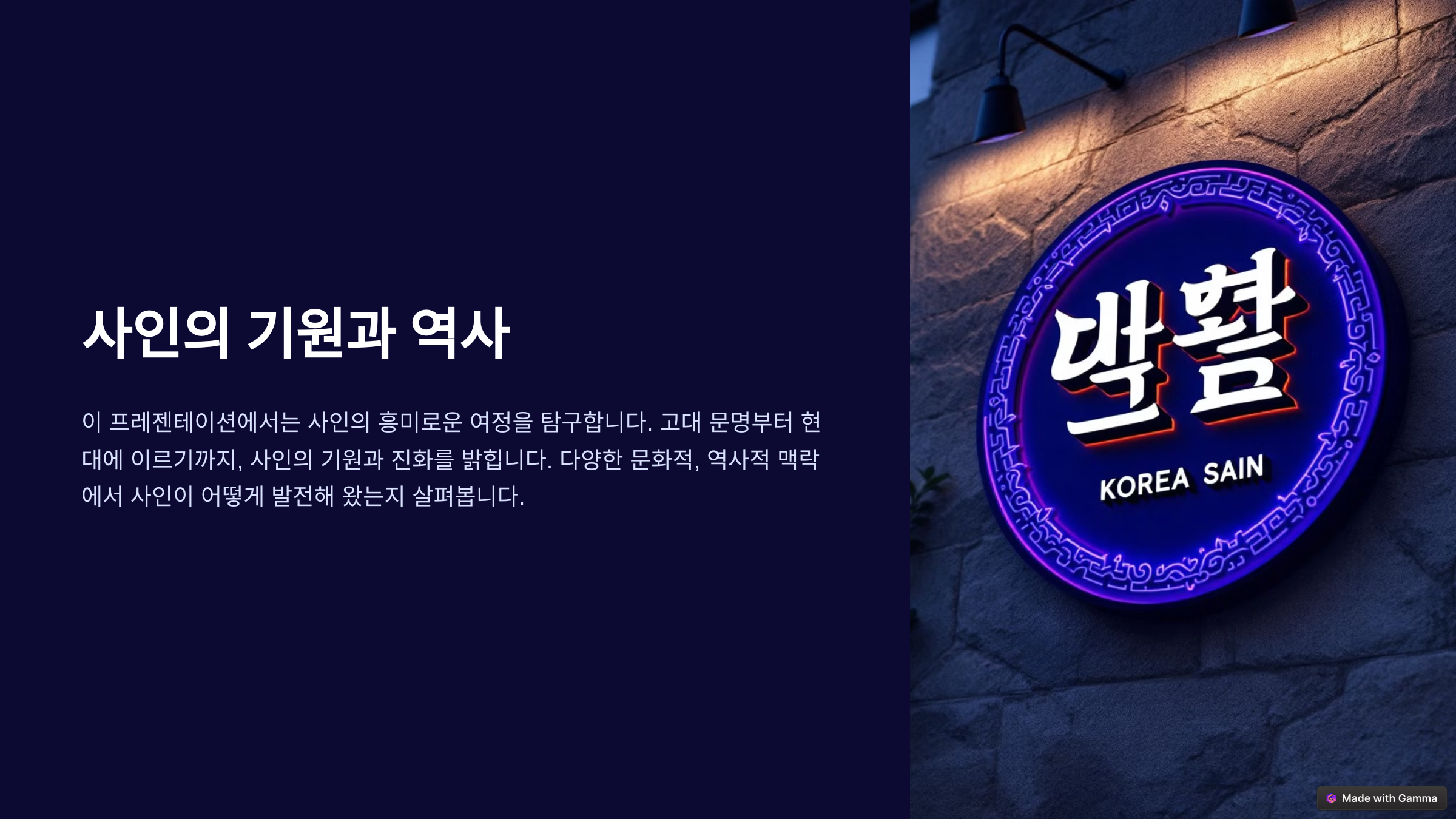
사인의 기원과 역사
광고 사인은 인류가 문자를 사용하기 이전부터 존재했어요. 원시시대 동굴벽화도 일종의 사인이었고, 고대 이집트에서는 상징 문양을 활용한 표지판을 사용했죠. 로마 시대에는 여관과 가게를 구분하기 위해 간판이 등장했고, 이때부터 본격적인 사인의 역사가 시작되었어요.중세 유럽에서는 문맹률이 높아서 문자 대신 그림을 이용한 간판이 유행했어요. 예를 들어, 대장간은 망치 그림을, 제빵사는 빵 그림을 간판에 넣었죠. 이 덕분에 누구나 쉽게 직업이나 상점을 알아볼 수 있었어요.
산업혁명 이후 기술이 발전하면서 금속, 네온, LED 등을 활용한 사인이 등장했어요. 특히 20세기 초 미국에서는 네온사인이 유행하며 도시의 야경을 화려하게 장식했죠. 현재는 디지털 디스플레이까지 접목되어 더욱 다양하고 세련된 사인들이 만들어지고 있어요.
📜 사인의 시대별 변천
시대 특징 고대 이집트 상형문자, 로마 상점 간판 중세 그림 간판 (빵, 망치 등 직업 상징) 산업혁명 금속 간판, 전등 사용 20세기 네온사인, LED 간판 21세기 디지털 디스플레이, 스마트 사인 사인은 단순한 표식이 아니라 시대의 변화와 기술 발전을 보여주는 중요한 요소예요. 오늘날에는 AI와 IoT를 활용한 인터랙티브 사인도 등장하면서 새로운 변화를 맞이하고 있죠. 나머지 내용도 계속해서 알아볼게요! 😉
📌 사인의 종류와 특성
사인의 종류와 특성 사인은 용도와 제작 방식에 따라 다양한 형태로 나뉘어요. 흔히 볼 수 있는 간판부터, 전광판, 공공시설 안내판, 브랜드 로고까지 모두 사인의 한 종류죠. 각각의 사인은 목적과 환경에 따라 최적의 재료와 디자인을 적용해야 해요.
예를 들어, 실외 간판은 날씨에 영향을 받기 때문에 내구성이 강한 재료가 필요해요. 반면, 실내 사인은 조명과 시각적 효과를 중시하는 경우가 많죠. 또한, 공공장소에서는 가독성이 중요한 요소로 작용해요.
사인의 특성을 이해하면 효과적인 메시지 전달이 가능해요. 이제 주요 사인의 종류와 특성을 한눈에 살펴볼까요?
🔍 주요 사인의 종류
사인 종류 특성 예시 간판 상점이나 기업의 대표적 표시 카페, 음식점 간판 전광판 LED 조명을 사용한 디지털 사인 타임스퀘어 광고판 공공 안내판 공공장소에서 길 찾기 및 정보 제공 지하철역 출구 안내 브랜드 로고 기업 아이덴티티를 나타내는 상징 애플, 나이키 로고 디지털 디스플레이 터치스크린, 인터랙티브 기능 포함 스마트 키오스크 이처럼 사인은 단순한 표지판이 아니라, 장소와 목적에 따라 맞춤형으로 제작되는 중요한 요소예요. 이제 사인의 디자인 원리에 대해 더 자세히 알아볼까요? 😊
🎨 사인 디자인 원리
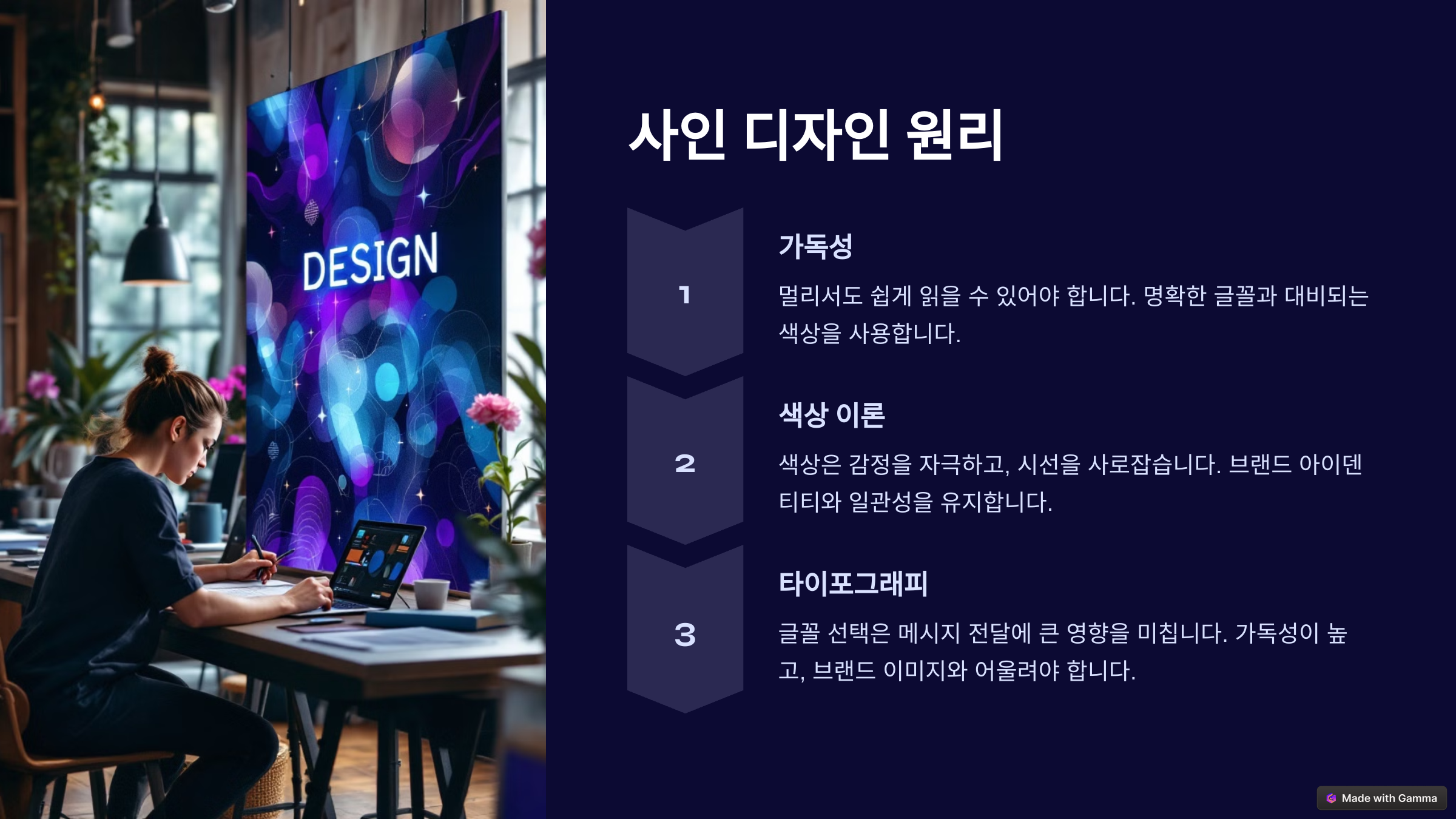
사인 디자인 원리 사인은 정보를 효과적으로 전달하는 것이 가장 중요해요. 단순히 예쁜 디자인이 아니라, 가독성과 시각적 균형을 고려해야 해요. 또한, 브랜드의 정체성을 반영하는 것도 필수 요소죠.
사인을 디자인할 때는 몇 가지 중요한 원칙이 있어요. 첫째, 명확하고 직관적인 텍스트를 사용해야 해요. 둘째, 색상 대비를 적절히 활용해서 가독성을 높여야 하죠. 셋째, 크기와 배치를 신중하게 결정해서 멀리서도 쉽게 인식될 수 있도록 해야 해요.
특히 야외 사인은 주간과 야간의 가독성을 모두 고려해야 해요. 네온사인이나 LED 조명을 활용하면 밤에도 효과적으로 메시지를 전달할 수 있어요. 이제, 효과적인 사인 디자인을 위한 주요 원칙을 정리해볼게요.
💡 효과적인 사인 디자인 원칙
디자인 원칙 설명 가독성 폰트 크기와 색상 대비를 고려해 쉽게 읽히도록 제작 색상 선택 배경과 텍스트 색상의 명암 대비를 높여 인식력 강화 위치 및 크기 멀리서도 잘 보이도록 크기와 배치를 최적화 브랜드 일관성 기업의 브랜드 색상과 로고를 반영하여 일관성 유지 조명 효과 네온, LED 등을 활용해 주야간 가독성을 향상 이처럼 사인의 디자인은 단순히 예쁘게 만드는 것이 아니라, 정보 전달과 가독성을 최우선으로 고려해야 해요. 이제 사인이 실제로 어떻게 제작되는지 살펴볼까요? 😊
🔨 사인의 제작 과정
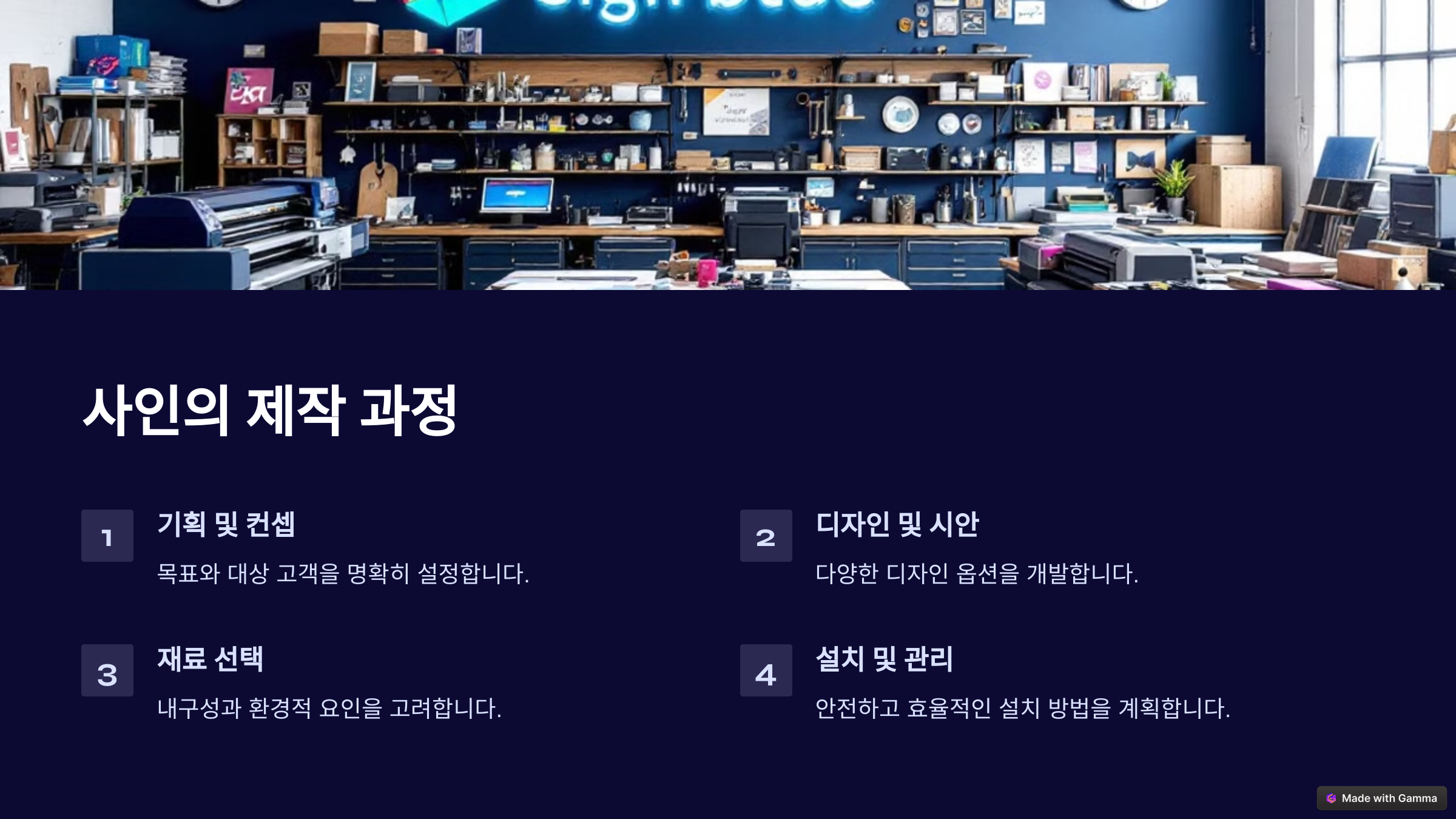
사인의 제작 과정 사인은 디자인이 완성된 후 다양한 공정을 거쳐 제작돼요. 소재 선택부터 가공, 조명 설치까지 여러 단계가 필요하죠. 각 과정은 사인의 내구성과 완성도에 직접적인 영향을 미쳐요.
예를 들어, 실외 간판은 비바람을 견뎌야 하므로 알루미늄이나 스테인리스 같은 내구성이 강한 재료를 사용해요. 반면, 실내 사인은 가벼운 아크릴이나 PVC 소재가 많이 쓰이죠. 조명 사인의 경우 LED나 네온 튜브를 추가해서 가시성을 높일 수 있어요.
이제, 사인의 제작 과정을 단계별로 정리해볼게요. 아래 표에서 자세한 정보를 확인해보세요!
🏗 사인의 제작 과정
단계 설명 1. 디자인 기획 고객 요구사항을 반영하여 디자인 제작 2. 소재 선택 실내·실외 환경을 고려한 재료 선정 3. 가공 및 제작 재료를 절단, 인쇄, 조립하는 과정 4. 조명 설치 네온·LED 등을 활용한 시각 효과 추가 5. 마감 및 테스트 완성된 사인의 내구성 및 기능 점검 6. 설치 및 유지보수 현장 설치 후 정기적인 관리 진행 이처럼 사인의 제작 과정은 세심한 계획과 기술이 필요해요. 좋은 사인은 단순한 표지판을 넘어 브랜드 아이덴티티를 강화하는 중요한 역할을 해요. 이제 실제 성공적인 사례를 분석해볼까요? 😊
📊 실제 사례 분석
실제 사례 분석 1 효과적인 사인은 브랜드를 각인시키고 고객의 행동을 유도하는 강력한 도구예요. 이번에는 유명한 사인 사례를 분석하면서 성공 요인을 살펴볼게요.
대표적인 사례로는 뉴욕 타임스퀘어의 디지털 전광판, 맥도날드의 골든 아치, 그리고 런던 지하철의 라운델(Roundel) 사인이 있어요. 이 사인들은 각각의 목적과 환경에 맞춰 최적화된 디자인을 적용했죠.
각 사례를 구체적으로 살펴보면서 어떤 요소들이 효과적인지 확인해볼까요?
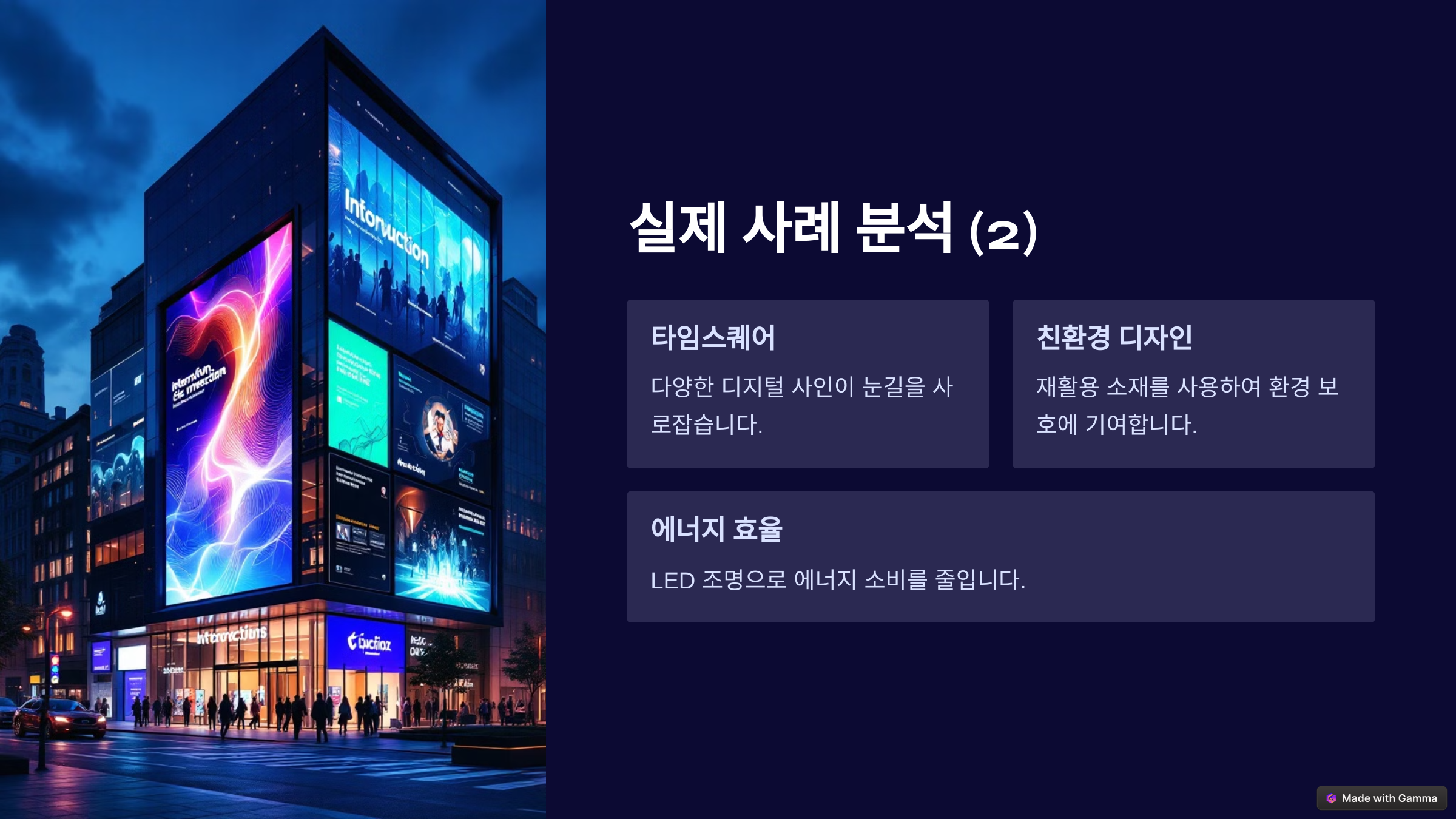
실제 사례 분석 2 🌟 성공적인 사인 사례
사례 특징 성공 요인 🗽 뉴욕 타임스퀘어 전광판 초대형 LED 광고판, 화려한 색상 주목성 극대화, 광고 효과 최적화 🍟 맥도날드 골든 아치 노란색 M자형 간판 심플한 디자인, 브랜드 아이덴티티 강조 🚇 런던 지하철 라운델 원형 디자인 + 파란 바탕에 붉은 글씨 가독성 극대화, 직관적인 안내 🏨 라스베이거스 네온사인 화려한 색상과 움직이는 조명 야간 가시성 우수, 관광 명소화 이 사례들을 보면 성공적인 사인은 단순히 정보 전달을 넘어 감성적인 연결까지 형성할 수 있다는 걸 알 수 있어요. 이제 미래의 사인 트렌드는 어떻게 변화할까요? 😊
🚀 미래의 사인 트렌드
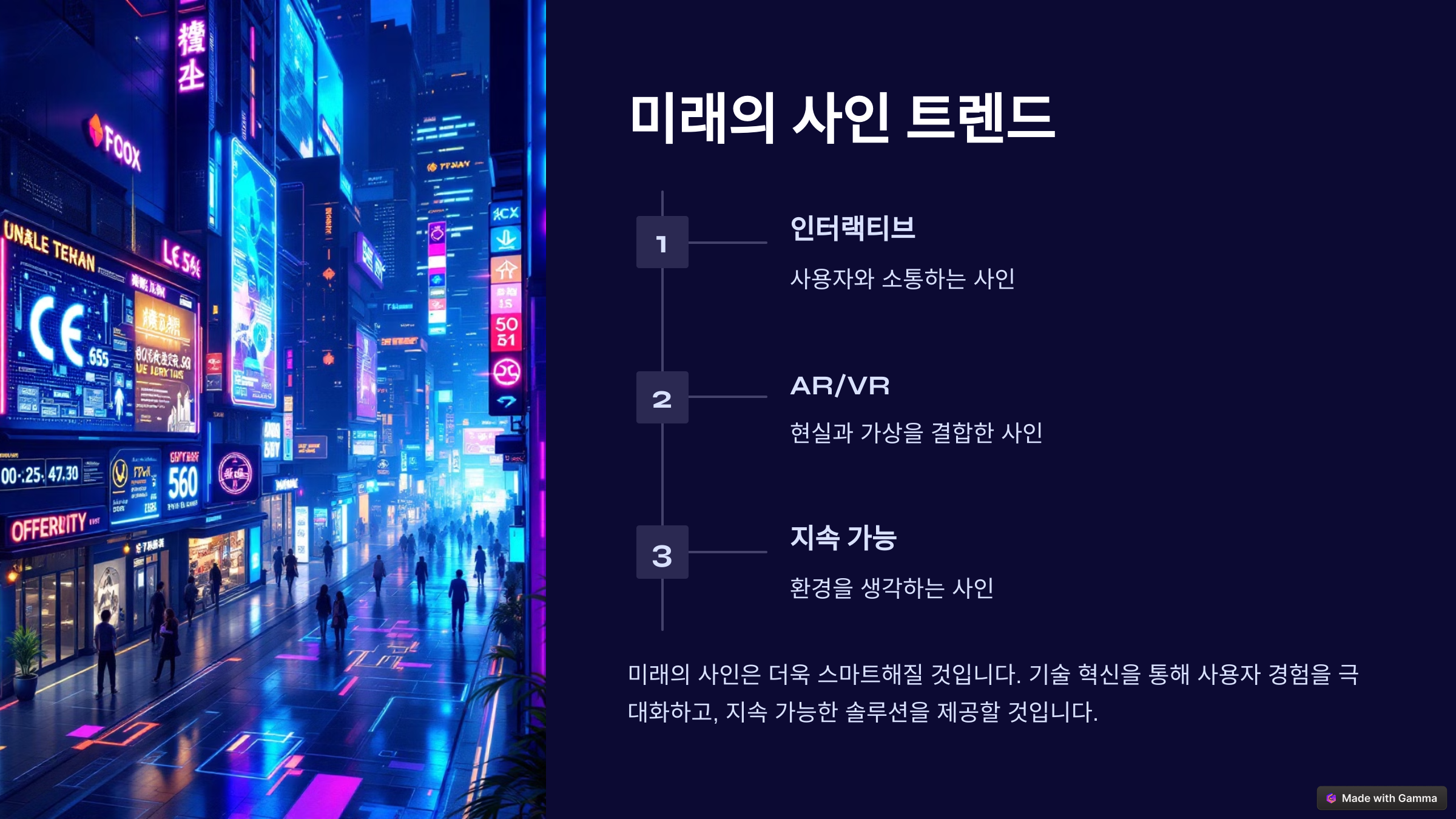
미래의 사인 트렌드 기술이 발전하면서 사인의 형태도 점점 더 혁신적으로 변화하고 있어요. 이제 단순한 표지판을 넘어서, 디지털 기술과 결합한 스마트 사인이 대세가 되고 있죠.
대표적인 예로는 AI(인공지능)를 활용한 맞춤형 광고판, 증강현실(AR) 기술을 적용한 인터랙티브 사인, 그리고 친환경 소재를 이용한 지속 가능한 사인이 있어요. 이러한 변화는 사인이 단순한 정보 전달에서 벗어나 사용자 경험을 극대화하는 방향으로 발전하고 있음을 보여줘요.
미래의 사인은 어떻게 변화할지 아래 표를 통해 정리해볼게요.
🔮 미래 사인의 주요 트렌드
트렌드 설명 🧠 AI 맞춤형 사인 사람의 행동과 관심사를 분석해 맞춤형 광고 제공 📱 증강현실(AR) 사인 스마트폰이나 AR 기기를 통해 가상 정보를 제공 🌱 친환경 사인 태양광, 친환경 소재를 활용한 지속 가능한 사인 🖥 인터랙티브 디지털 사인 사용자와 상호작용하는 터치스크린 및 음성 인식 기능 포함 🌍 글로벌 스마트 사인 다국어 지원 및 실시간 번역 기능 탑재 내가 생각했을 때, 미래의 사인은 단순히 정보를 제공하는 역할에서 벗어나 사용자와 소통하고, 더 나아가 환경까지 고려하는 방향으로 발전할 것 같아요. 점점 더 스마트해지는 사인의 세계, 앞으로가 기대되지 않나요? 😊
❓ FAQ (자주 묻는 질문)
Q1. 사인의 디자인에서 가장 중요한 요소는 무엇인가요?
A1. 가독성이 가장 중요해요! 글씨 크기, 색상 대비, 조명 효과 등을 고려해야 사람들이 쉽게 인식할 수 있어요.
Q2. 사인을 제작할 때 비용은 얼마나 드나요?
A2. 크기, 재질, 조명 여부에 따라 천차만별이에요. 일반적인 간판은 50만 원~200만 원, LED 전광판은 수백만 원 이상 들 수 있어요.
Q3. 실내 사인과 실외 사인의 차이는 무엇인가요?
A3. 실외 사인은 내구성이 강한 소재(알루미늄, 스테인리스)를 사용하고, 실내 사인은 경량 소재(PVC, 아크릴)를 주로 사용해요.
Q4. LED 사인과 네온사인의 차이점은?
A4. LED 사인은 에너지 효율이 높고 유지보수가 쉬워요. 네온사인은 따뜻한 느낌을 주지만 전력 소모가 크고 관리가 어려워요.
Q5. 친환경 사인은 어떤 방식으로 제작되나요?
A5. 태양광 패널을 활용한 전력 공급, 재활용 가능한 소재(목재, 친환경 플라스틱)를 사용하는 방식으로 제작돼요.
Q6. 사인 제작 기간은 얼마나 걸리나요?
A6. 디자인 복잡도와 크기에 따라 다르지만, 일반적으로 1~2주 정도 걸려요. 대형 전광판의 경우 1개월 이상 소요될 수도 있어요.
Q7. AI 기반 스마트 사인은 어떻게 작동하나요?
A7. 카메라와 센서를 활용해 사람의 움직임이나 관심사를 분석하고, 실시간으로 맞춤형 광고나 정보를 제공해요.
Q8. 사인을 오래 유지하려면 어떻게 관리해야 하나요?
A8. 정기적으로 청소하고, 전자 부품이 있는 경우 방수 처리를 해야 해요. 특히 야외 사인은 기후 변화에 따른 점검이 필수예요.